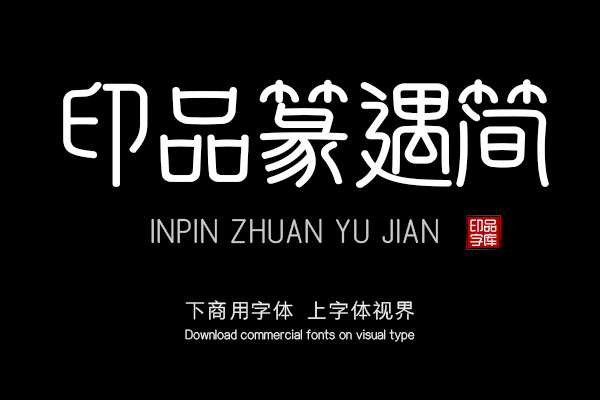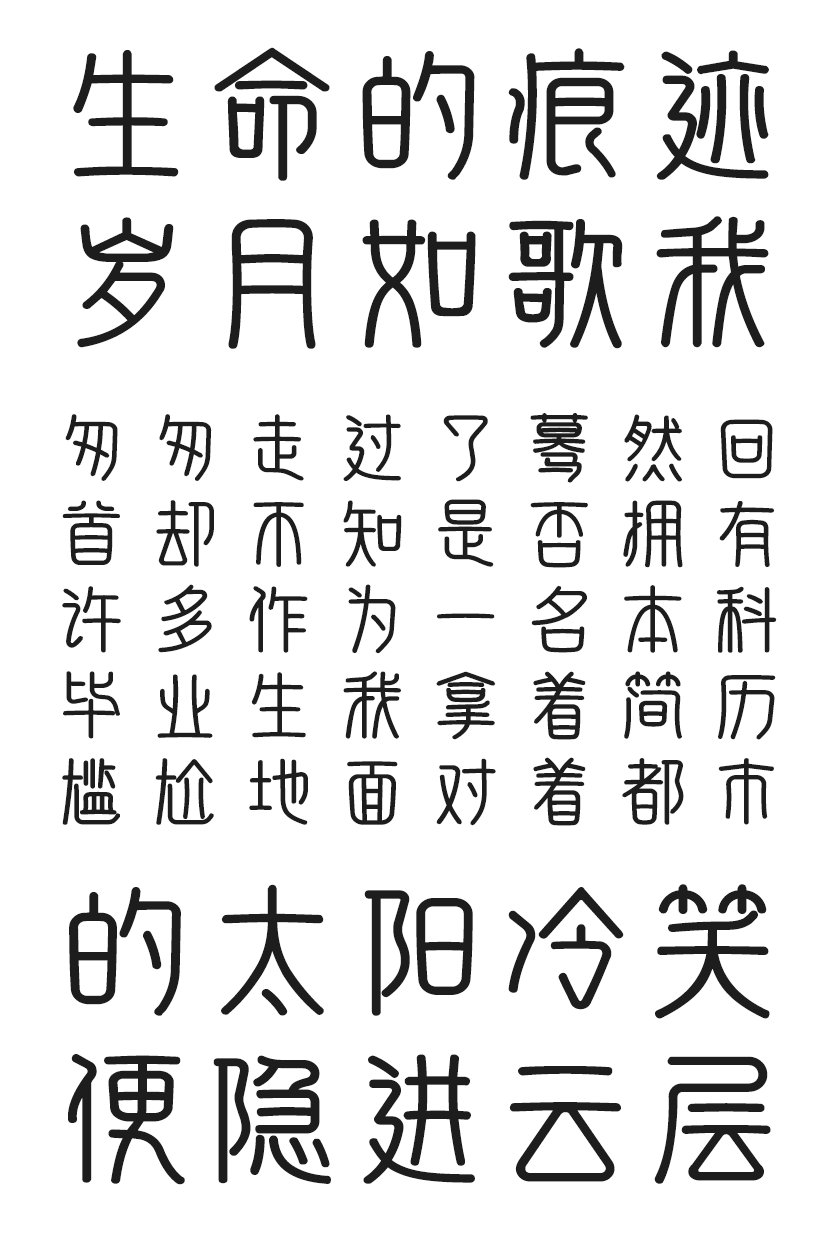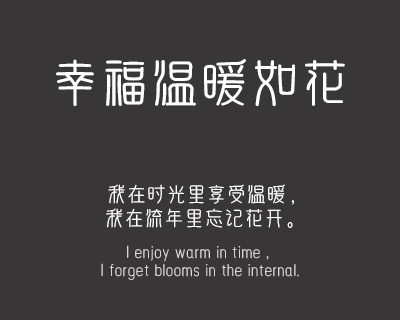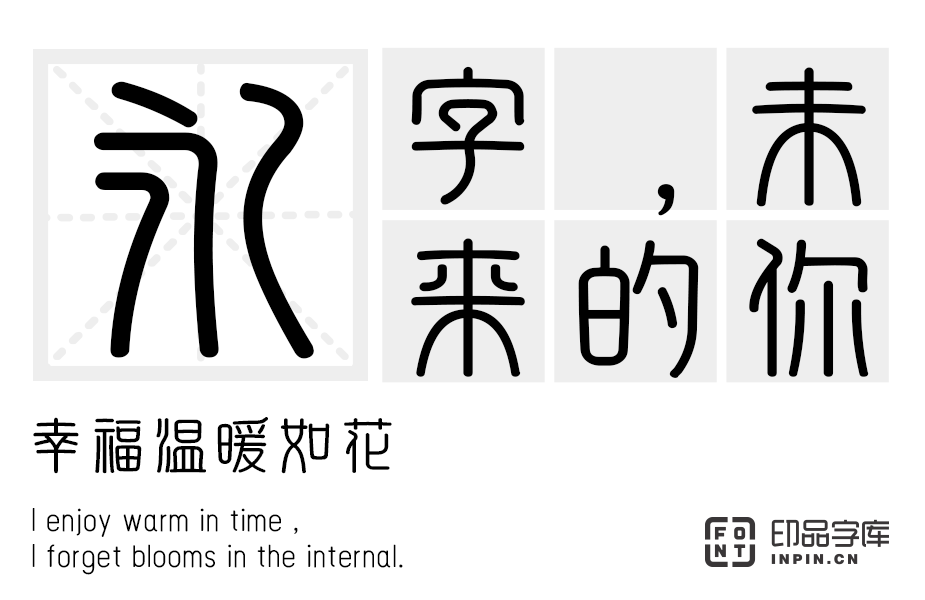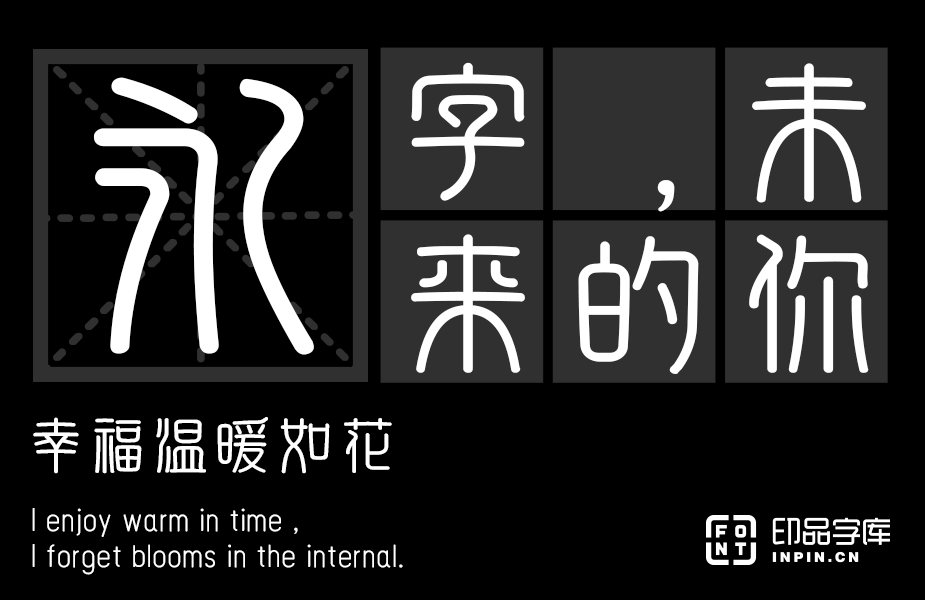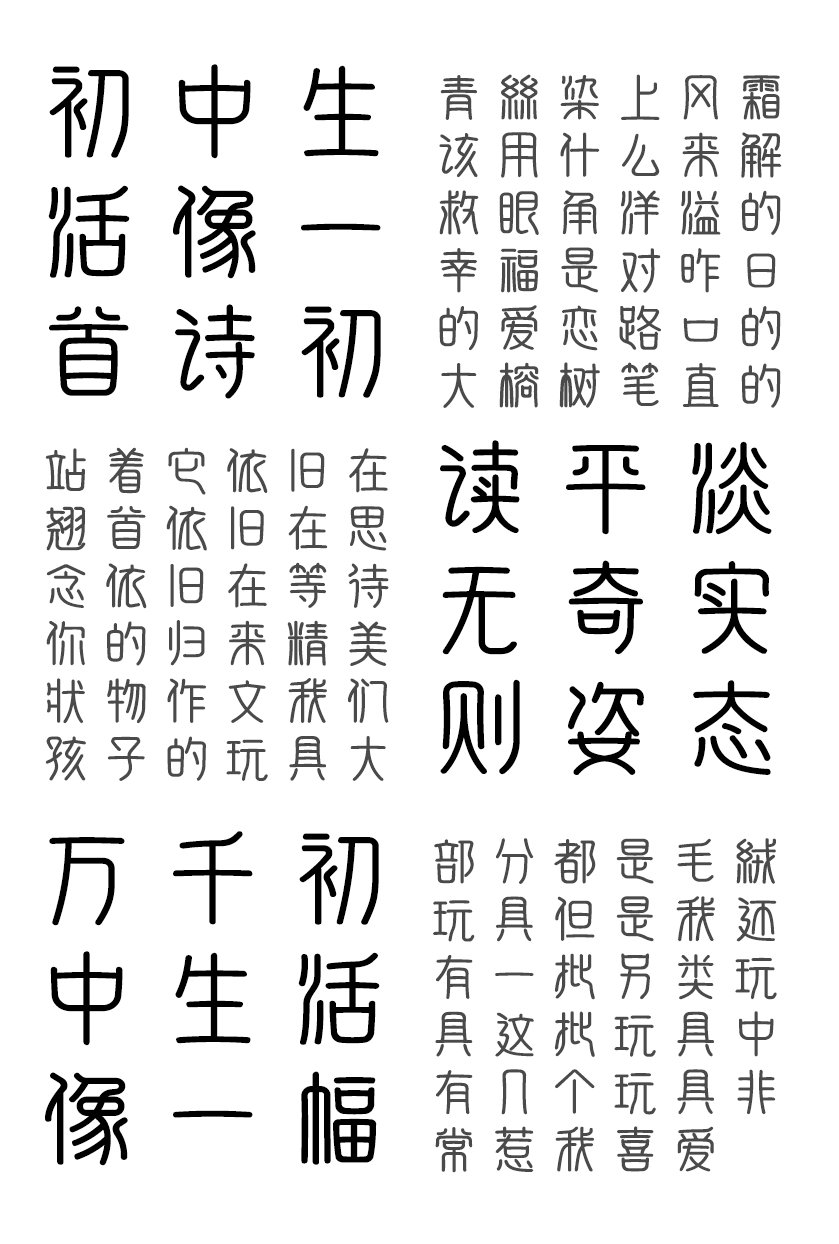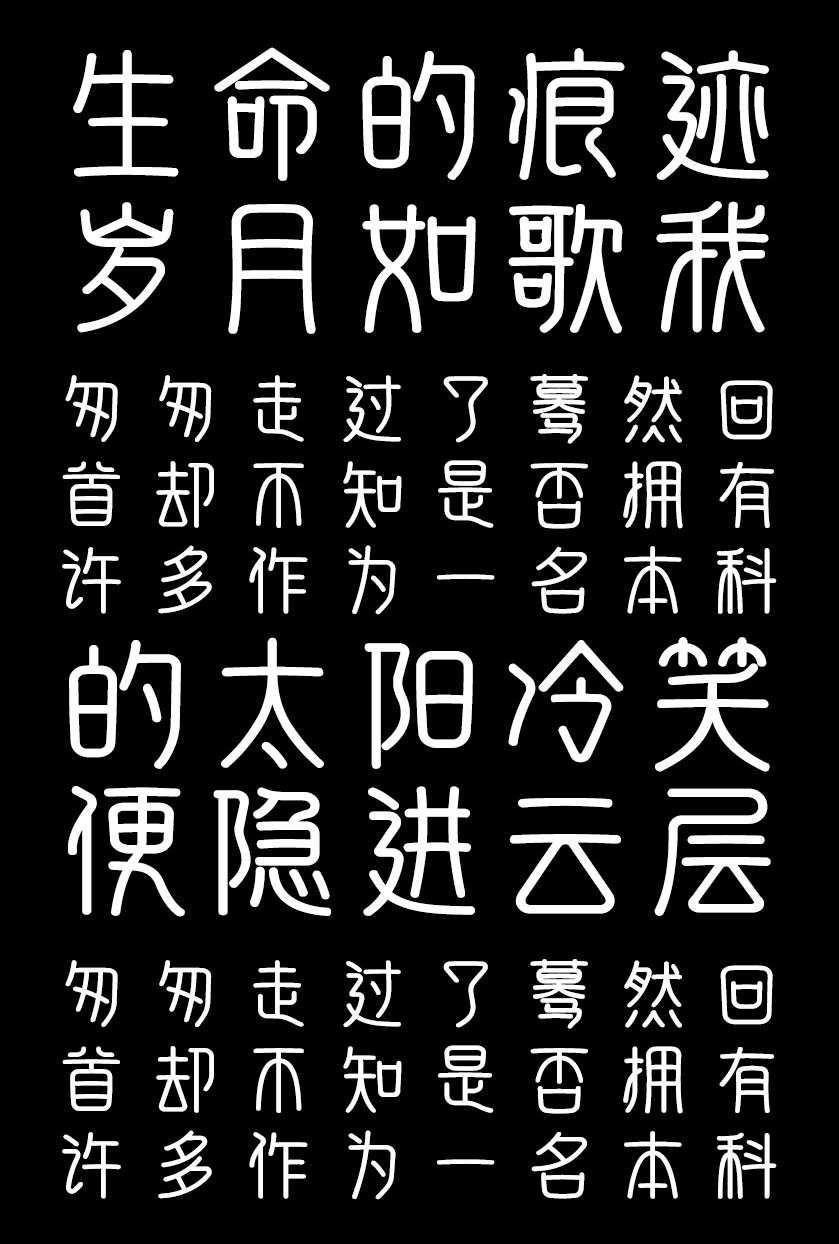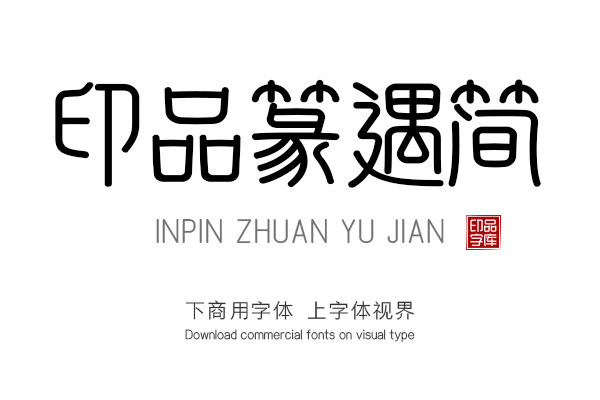
印品篆遇简的创作灵感来源于篆体。秦始皇统一中国后,统一了全国文字。篆体,又称“篆书”,虽然和现在的简体字有很大的区别,但是其字体非常优美,为了让现代人可以使用篆体般优美又易识别的字体,设计师认真地研究了篆体。然后设计出了这款印品篆遇简字体。 此款笔画横平竖直,圆劲均匀,粗细基本一致。所有横画和竖画等距平行,所有笔画以圆为主,圆起圆收,方中寓圆,圆中有方,使转圆活,富有奇趣。 篆尚婉而通,为了更适合小屏的显示,设计师适当减少了上下部分的比例,减少了字体下面垂脚的长度; “印品篆遇简”不仅保留了篆书原有的特征,同时也融入了设计师自己的设计灵感,使得这款字体更符合现代阅读需求,用户在使用这款字体的时候不仅可以在日常毫无障碍阅读,更可以感受到篆书的魅力。